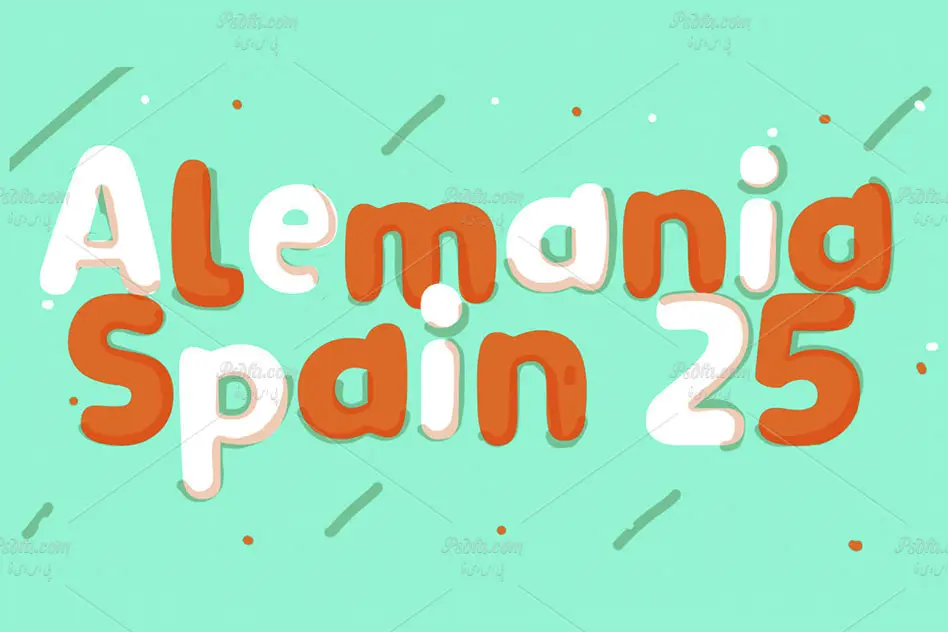
فونت انگلیسی کارتونی و کودکانه کلارنس Clarence English Font
فونت انگلیسی کارتونی و کودکانه کلارنس
در این پست شاهد فونت انگلیسی کارتونی و کودکانه کلارنس Clarence English Font مناسب جهت ایجاد طرح های کودکانه می باشید. این فونت زیبا در قالب یک فایل otf در سایت قرار گرفته است که با نصب این فایل در پوشه فونت های سیستم قادر به استفاده از آن در تمام نرم افزارهای گرافیکی و ویرایشگر متن از جمله نرم افزار فتوشاپ ، مجموعه نرم افزار آفیس و … خواهید بود. از این فونت زیبا که در تیتراژ کارتون کلارنس استفاده شده است می توانید در طرح های فانتزی و کودکانه از جمله طراحی کارت پستال ، طراحی انواع پوستر ، طراحی بر روی پارچه و لباس ، انیمیشن سازی و … استفاده نمود.